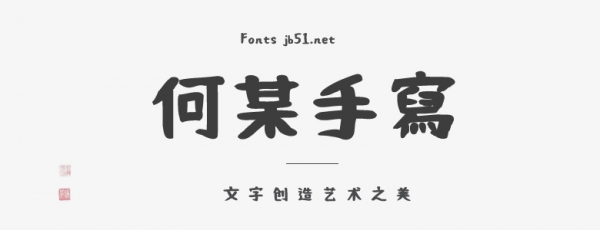
何某手寫(xiě)體是Max基于日本的おつとめフォント字體增補(bǔ)修改而成的一款隨心所欲的手寫(xiě)體。與原作者的主要差異是調(diào)整部件寫(xiě)法、新增中文字、增加為5個(gè)字重、增加一些符號(hào)。經(jīng)過(guò)Max的增補(bǔ),何某手寫(xiě)體對(duì)簡(jiǎn)體的字體支持也挺不錯(cuò)的。適用于平面宣傳設(shè)計(jì)、網(wǎng)頁(yè)設(shè)計(jì)、海報(bào)設(shè)計(jì)等應(yīng)用。